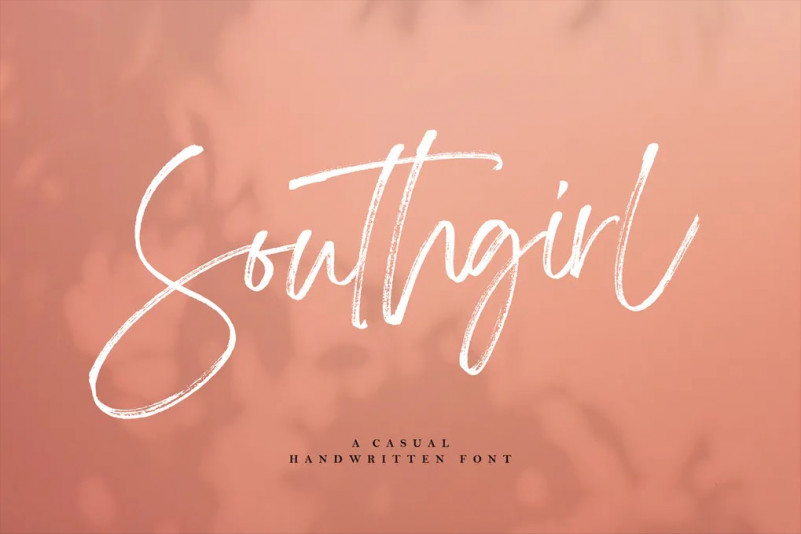
Southgirl Font
Présentation de nouvelles Police Southgirl Handwritten Font sont des Police Hanwritten avec des textures stylo à pinceau de style pentel que vous pouvez utiliser pour améliorer votre travail.
Southgirl Handwritten Font est disponible en 3 différents types de lettres minuscules, vous pouvez le changer comme vous le souhaitez pour créer un style unique lorsque plusieurs caractères de la même lettre se retrouvent. Et ce sera un avantage pour rendre votre écriture vraiment comme l’écriture manuscrite.